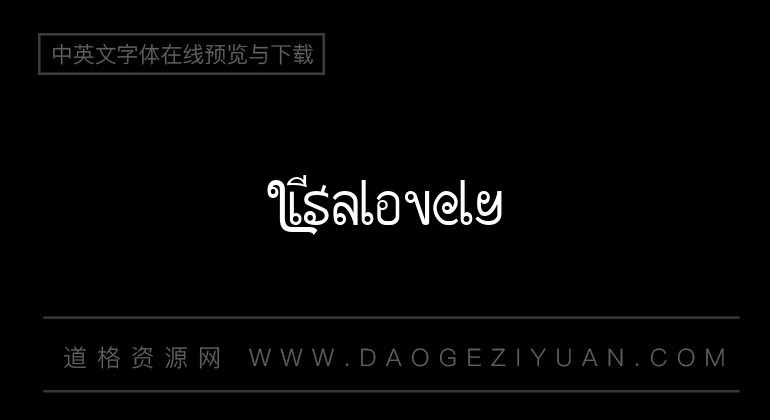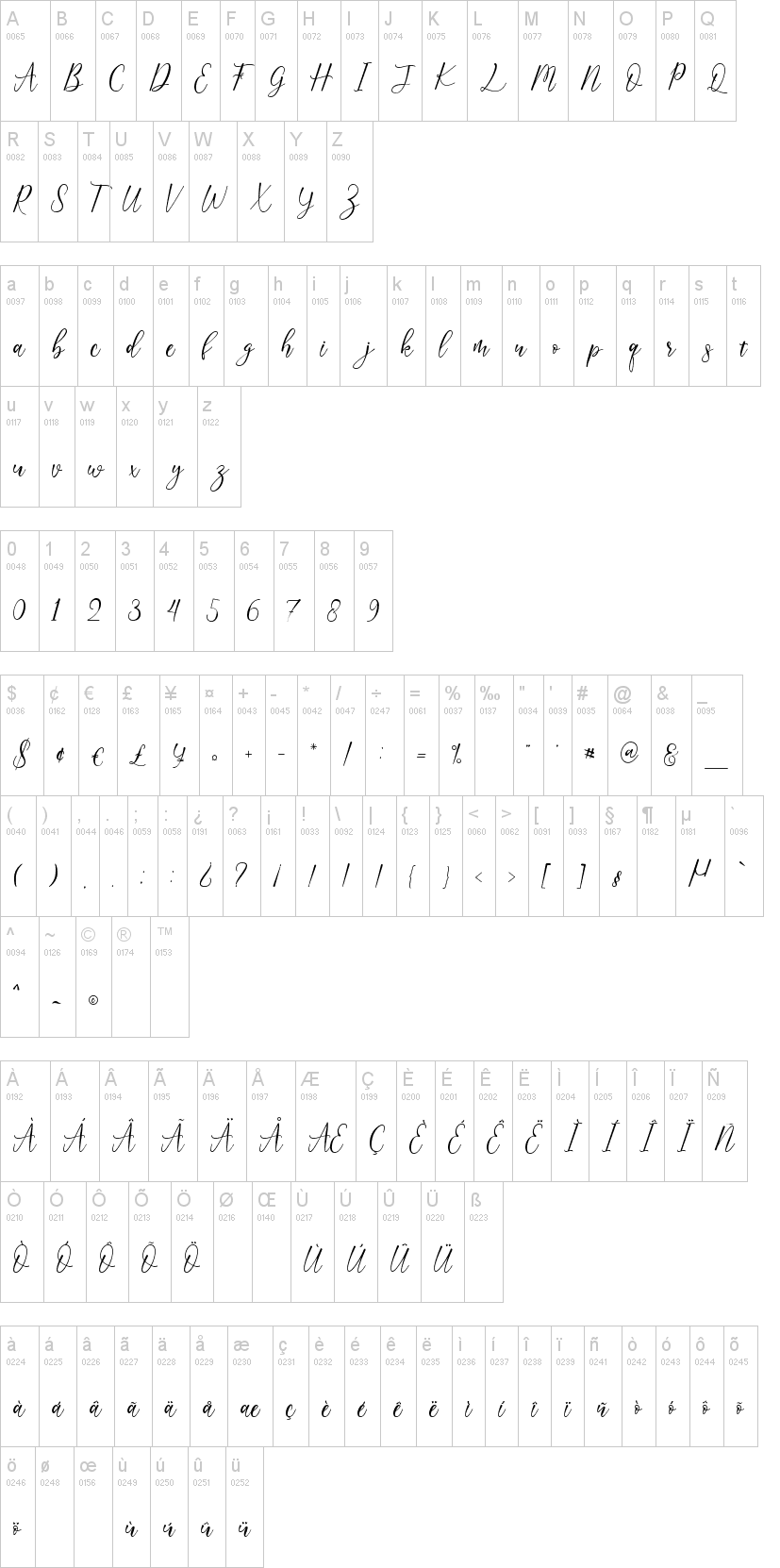
Lisalovely 是一种优美、精致的手写字体,具有优雅而流畅的曲线和线条。它由设计师 MySunday 于2018 年创作,是一种基于拉丁字母的连笔手写字体。 Lisalovely 字体非常适合用于标题、标志、印刷品、卡片、海报、包装等设计项目中,它的设计风格非常时尚、现代和轻松。该字体包含大写字母、小写字母、数字、标点符号和特殊符号,可在不同的设计场景中使用。 Lisalovely 字体的特点包括其优美的曲线和流畅的线条,以及其精致的设计和优雅的外观。如果你需要一种具有独特设计风格的手写字体,Lisalovely 可能是一个不错的选择。内容介绍
Lisalovely是一款非常不错的手写艺术字体,具有很好的视觉感,适合于文化类的宣传设计、商业类品牌的广告和产品包装设计以及个性化文字排版等较多场景。